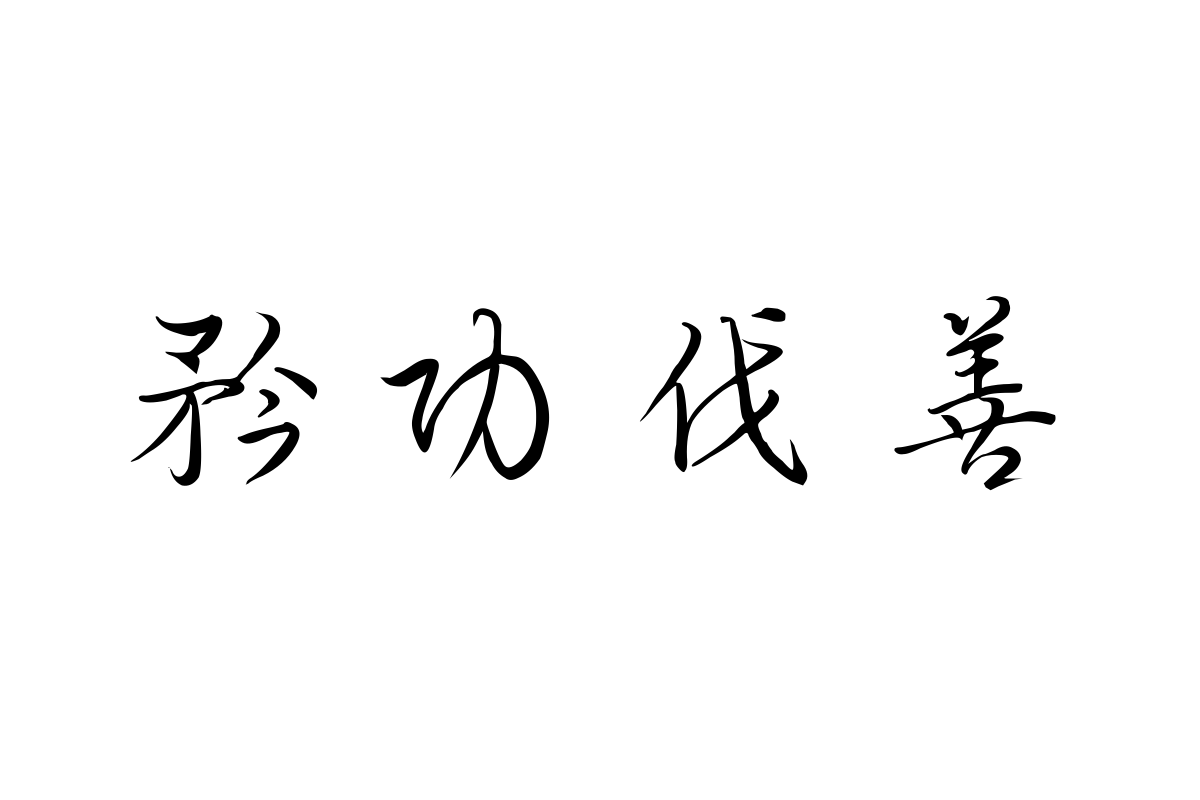
文道梅花体是一套由中国书法家文道先生设计的书法字体。这套字体以其独特的风格和韵味,深受广大书法爱好者的喜爱。以下是对文道梅花体的详细介绍:
1. 字形结构:文道梅花体的字形结构独特,笔画流畅自然,既有传统书法的韵味,又不失现代感。字体中融入了梅花的元素,使得整个字体更加富有艺术气息。
2. 字体特点:文道梅花体的字体特点主要体现在笔画的粗细变化上。在书写时,可以根据需要调整笔画的粗细,以展现不同的书写效果。同时,字体中的每个字都采用了不同的笔顺,使得整幅作品更具层次感。
3. 适用场景:文道梅花体适用于各种场合,如书法创作、书法教学、书法展览等。无论是个人练习还是专业展示,这套字体都能展现出独特的魅力。
4. 学习资源:为了更好地学习和掌握文道梅花体,可以查阅相关的书法教程和资料,了解其笔画技巧、结构特点等方面的知识。此外,还可以参考一些优秀的书法作品,以便于更好地理解和模仿。
总之,文道梅花体是一款具有独特风格和韵味的书法字体,适合广大书法爱好者进行学习和欣赏。通过学习和实践,相信您一定能掌握这套字体的魅力,将其融入到您的书法创作中。